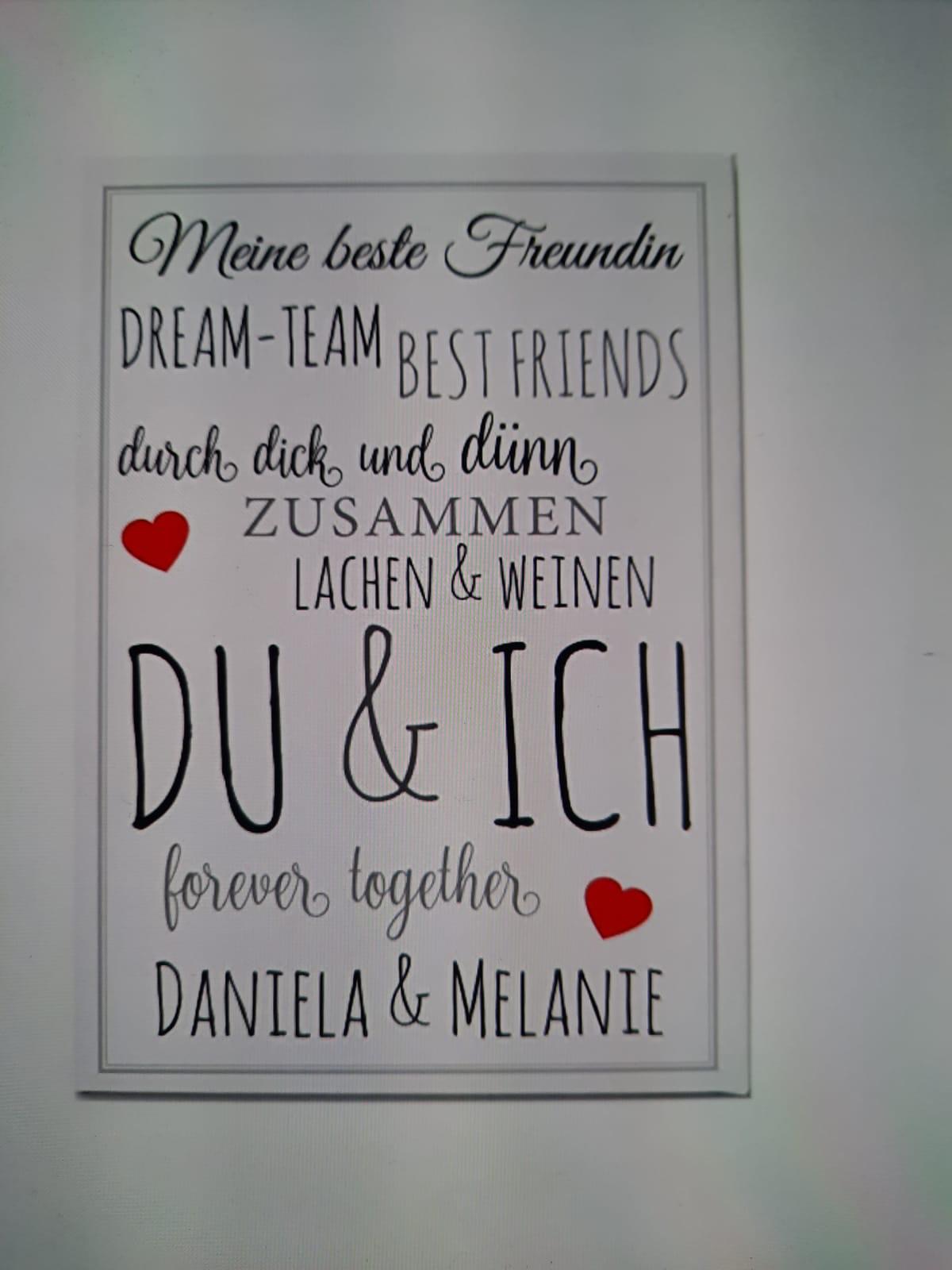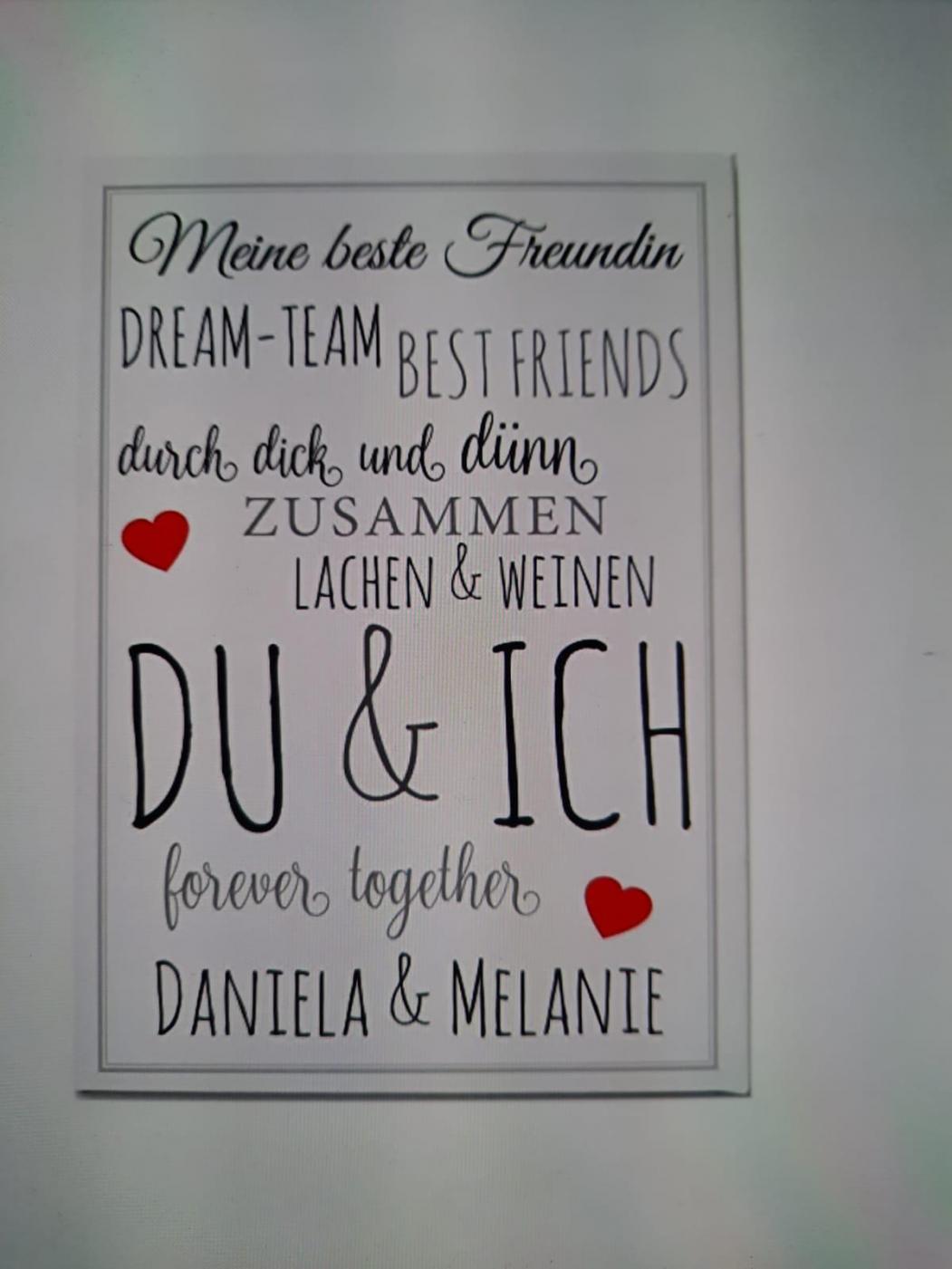
Suche Schrift von Geschenktafel
Eine Bekannte hat mir diesen Screenshot der Tafel geschickt. Druck auf Holz (evtl. von T...D..I?)
und hätte ihn gerne auf einer Schiefertafel als Geschenk für ihre Freundin sublimiert. Nun stehe ich vor der Herausforderung die Schriften zusammenzusuchen, da ich es ja möglichst genau nachbauen soll. Bis auf den Font der Zeilen "durch dick und dünn" und "forever together" habe ich alles gefunden.
Wisst ihr Rat?
Sie ist schon ähnlich bei "forever together", aber ich finde einfach keine Schrift, die diese speziellen Abschlüsse bei "durch dick und dünn" hat...
Wenn du in meinem link auf "View all Glyphs" klickst, führt dich das zu einer Übersicht sämtlicher Varianten, siehe Ralfs Erklärung.